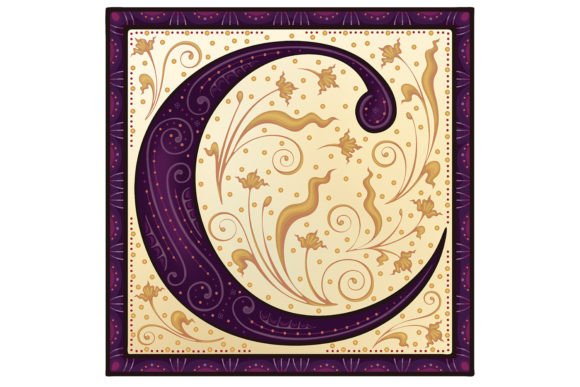
Initial Letters C.Alphabet.Typeface.
Initial Letters C.Alphabet.Typeface.μ κ°μ κ³ νμ§ μμ°μ μ°Ύκ³ μλ€λ©΄ μ΄ ν리미μ ν¨ν€μ§λ μ°½μμ μΈ νλ‘μ νΈλ₯Ό μν νμμ μΈ μ νμ λλ€.